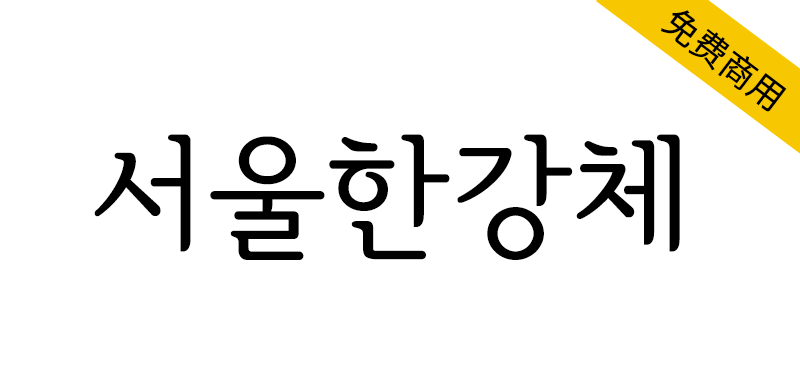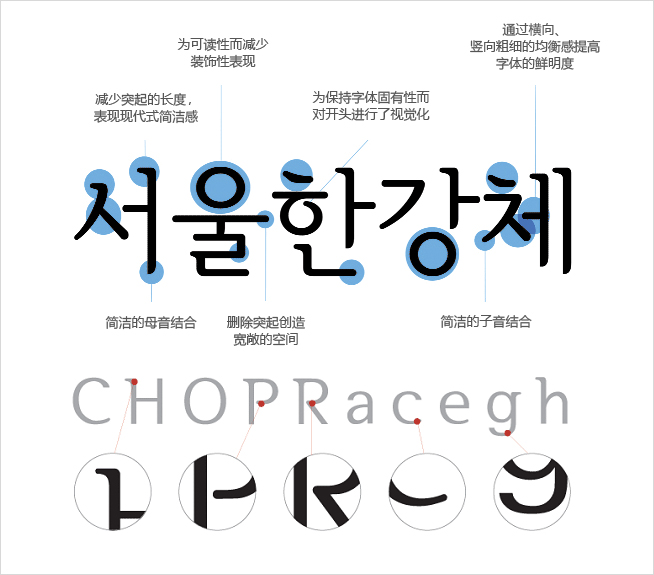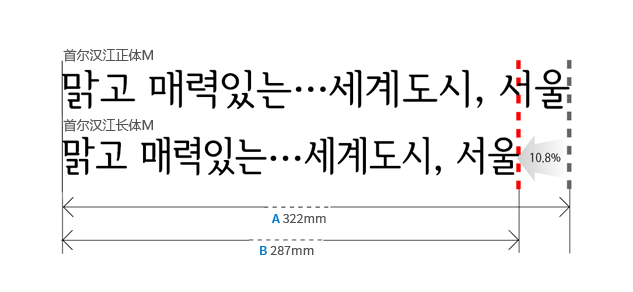
为普及首尔的固有字体,提升城市认同性与品牌价值,韩国首尔市开发出了明体系列的4种首尔汉江体(Light、Medium、Bold、Extra Bold)。
首尔字体中蕴含着刚正的儒士精神和淡雅的留白之美,从造型上展现了韩屋的开放和瓦片的曲线美。此外,首尔字体取名时采用首尔两大代表性资源之一的“汉江”,更能激发市民对韩民族固有美丽语言——韩文的文化自豪感。
首尔市将首尔字体作为首尔的固有字体而推广使用,首尔字体可提高城市认同性和品牌价值,开发了
首尔汉江体4种(Light、Medium、Bold、Extra Bold)
首尔汉江长体5种(Light、Medium、Bold、Extra Bold、black)。
首尔字体蕴含着正直的儒生精神和端庄典雅的含义,在造形上体现出韩屋的开放性和屋瓦的曲线美。
此外,字体名称运用了首尔代表性资源之一的“汉江”,首尔字体将提高韩民族固美丽语言——韩文的文化自豪感。
减少突起的长度,表现现代式简洁感
为提高可读性而减少装饰性笔画
为保持字体固有性而对开头进行了视觉化
通过横向、竖向粗细的均衡感提高字体的鲜明度
简洁的母音结合
删除突起部分,创造宽敞空间
简洁的子音结合